漢字と仮名の組み替え04「フィットフォントで組み替え」
タイププロジェクトのwebサイトにあるフィットフォントのシミュレーターは、和文と欧文の組み替えだけでなく、漢字と仮名の組み替えにも対応しています。
フィッティングの手順ですが、例えばフォントAをベースに仮名だけをフォントBに組み替えるとして、私の場合は、まずフォントBの仮名の太さや字幅をフォントAの仮名に近づけるところから始めています。近づけた仮名を組替えてから微調整して、表示サイズを小さくしたり大きくしたりして確認し、安定した組版に見えたら完成です。
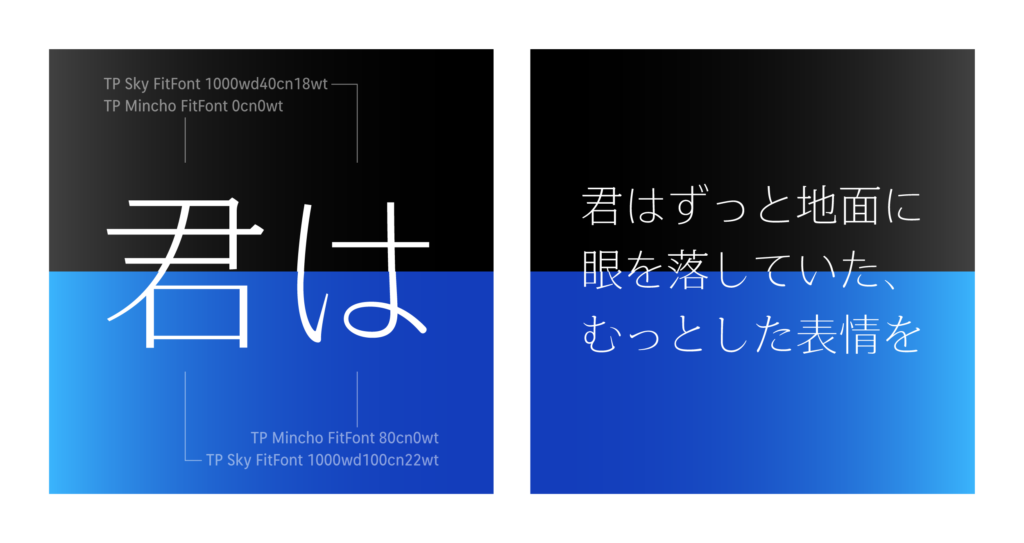
今回の画像はタイププロジェクト公式Instagramより担当Kがフィッティングしたフィットフォント同士の漢字仮名組み替えサンプルです。サンセリフ体のTPスカイと明朝体のTP明朝という違う系統同士の組み合わせが、ウェイトやコントラストの調整によって馴染んでいます。組み替えしない時の組版とイメージが変わって、新しい利用シーンが広がりそうです。